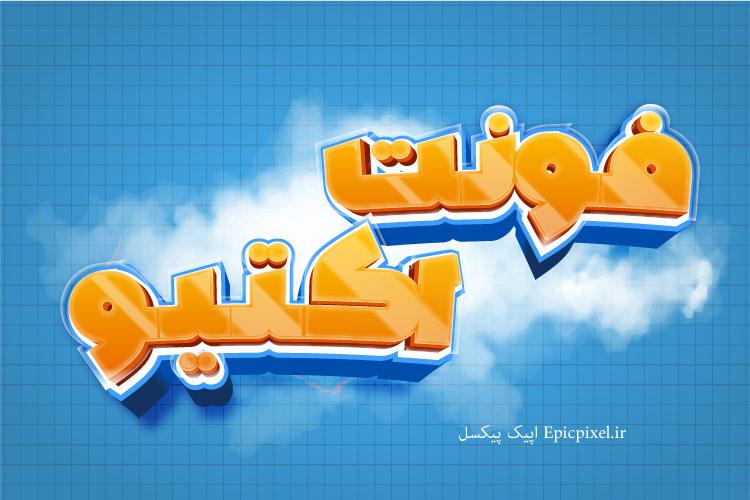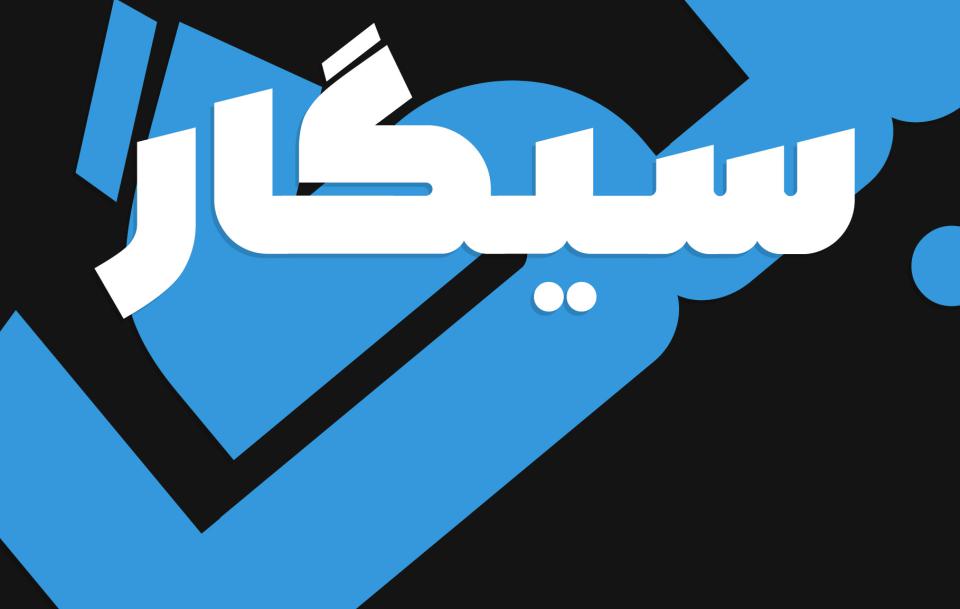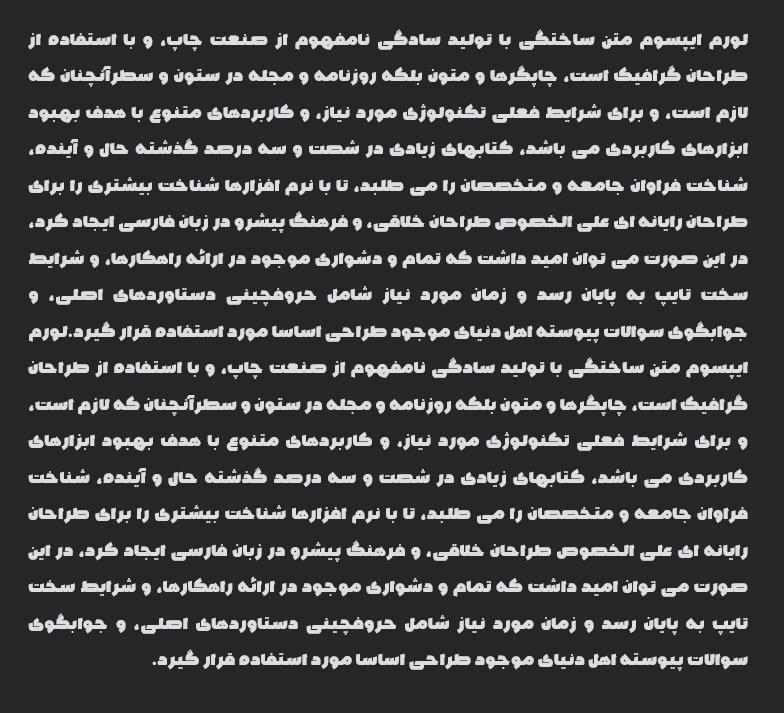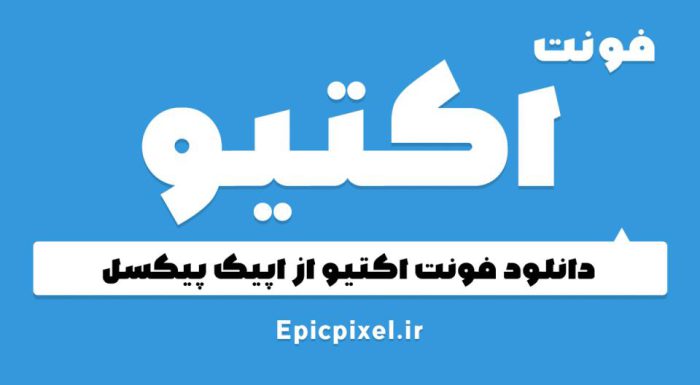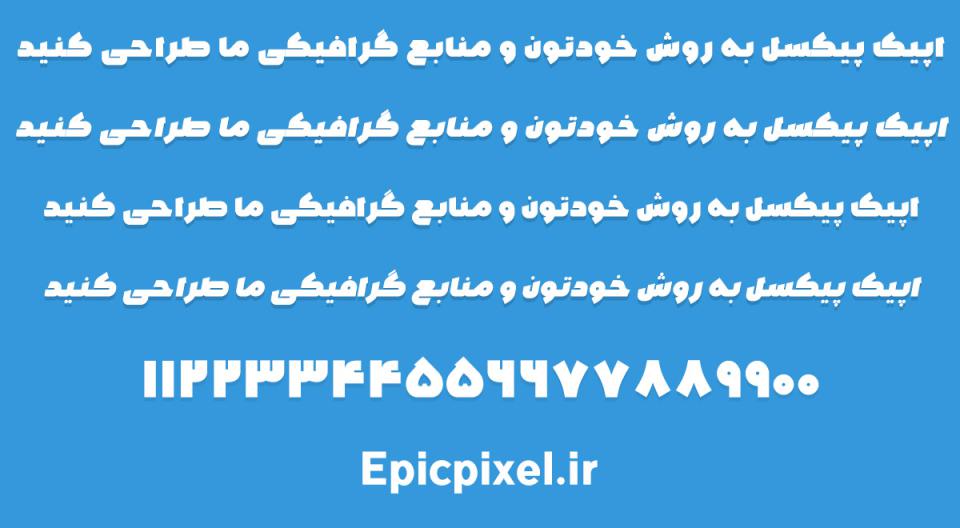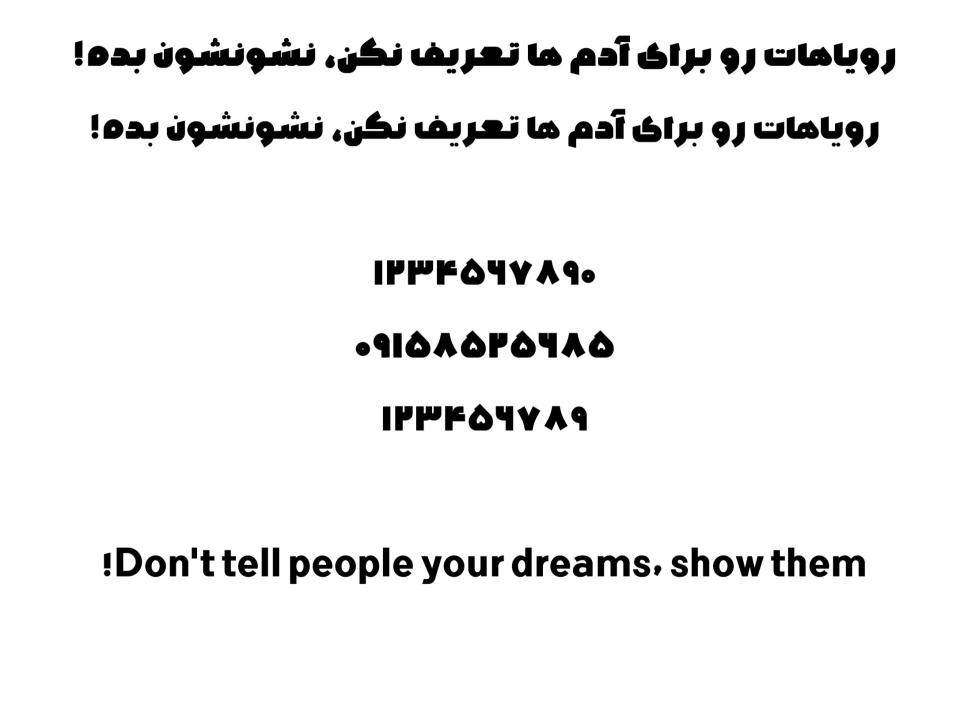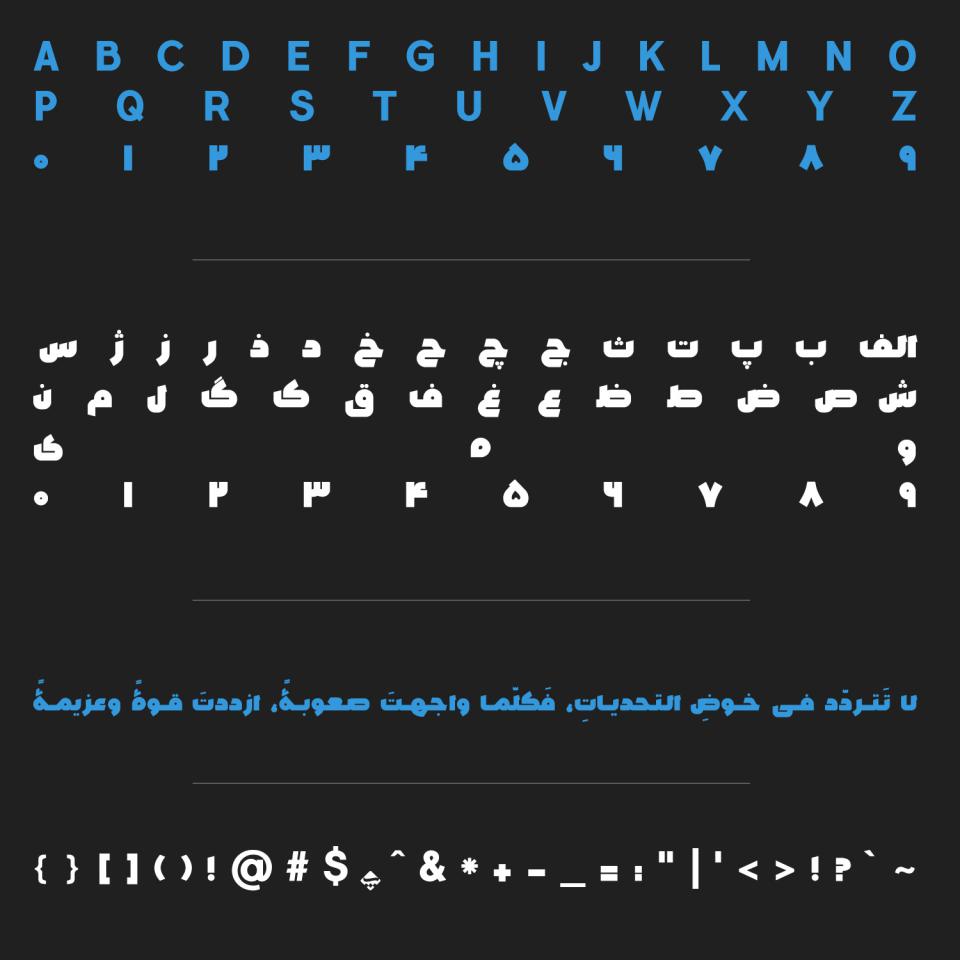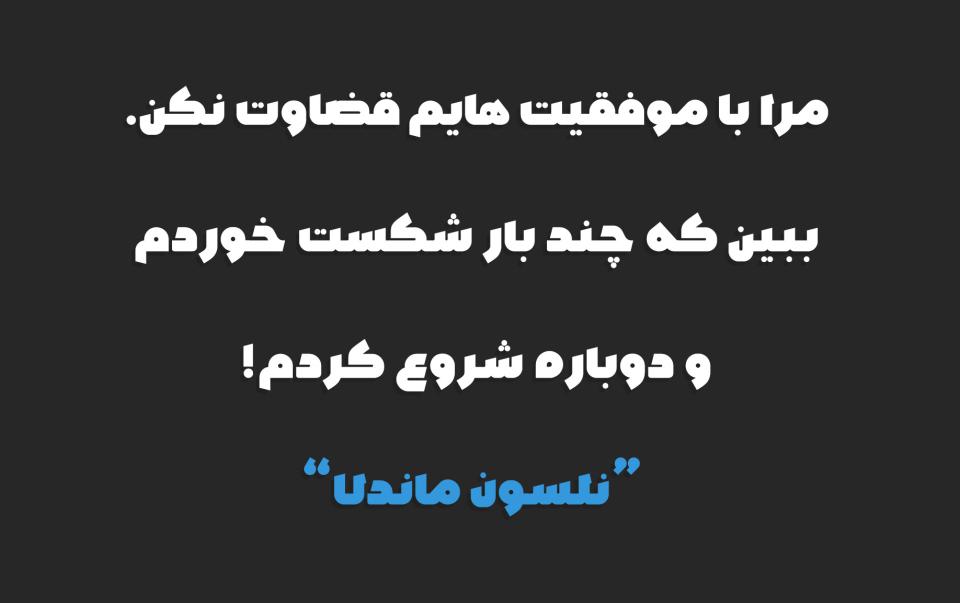
2 فونت اکتیو فارسی
فونت فارسی اکتیو؛ انتخابی جسورانه برای طراحی های شما
فونت اکتیو، یک فونت فارسی با طراحی جسورانه و ساختار محکم است که برای جلب توجه مخاطب طراحی شده است. این فونت با ترکیب هوشمندانه خطوط منحنی و مستقیم، ظاهری مدرن و جذاب به طراحی های شما می بخشد.
ویژگی های کلیدی فونت اکتیو:
- طراحی جسورانه و مدرن
- مناسب برای انواع پروژه های گرافیکی
چرا فونت اکتیو؟
اگر به دنبال فونتی هستید که به طراحی های شما هویت و شخصیت ببخشد، فونت اکتیو انتخابی ایده آل است. این فونت با ظاهری منحصربه فرد و کاربردی، به شما کمک می کند تا طرح هایی جذاب و ماندگار خلق کنید.
| ⭐ مجموعه فونت | Font Epic Active Bold Epic Active heavy |
| ⭐ توضیحات | فونت شبیه سازی شده اپیک اکتیو |